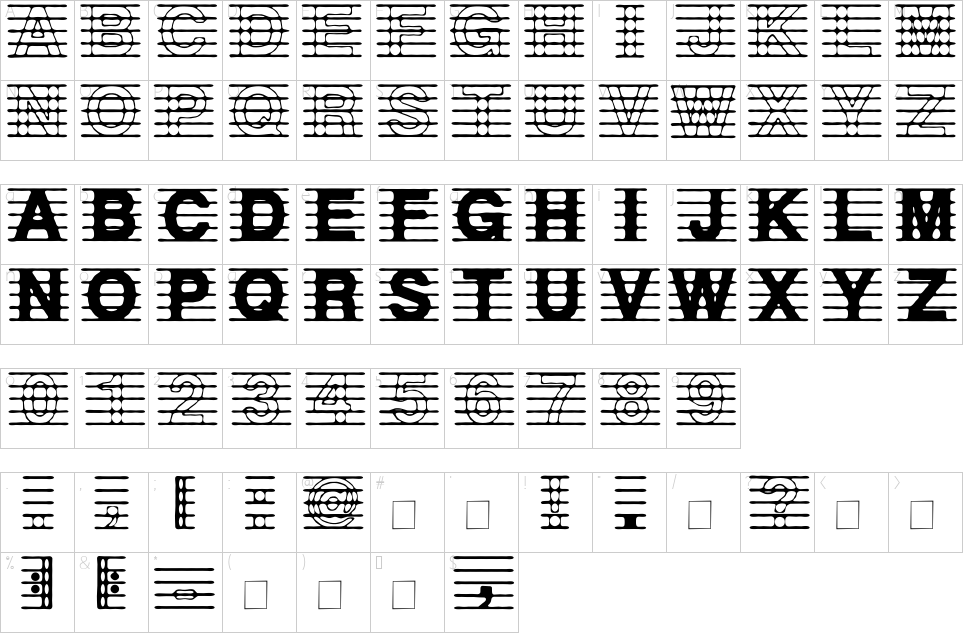
Descubra Distracted Musician Font, uma fonte única que enriquece seu projeto com um toque desconcentrado musical. Desenhada pela Anke-Art, esta fonte é perfeitamente adaptável tanto para dispositivos Windows quanto para Mac. Com seu design único e original, a Distracted Musician é uma escolha ideal para designers gráficos que procuram novas ideias de visualização para seus materiais. Se você está buscando adicionar um toque único e intrigante a suas criações digitais com apenas um clique, Distracted Musician Font pode ser sua escolha. Download esta fonte grátis para Windows e Mac e tenha à disposição uma opção divertida e inovadora para dar vida ao seu design. Com mais de 13 mil downloads, está provado que este é um recurso gráfico versátil e emocionante que vale a pena experimentar.